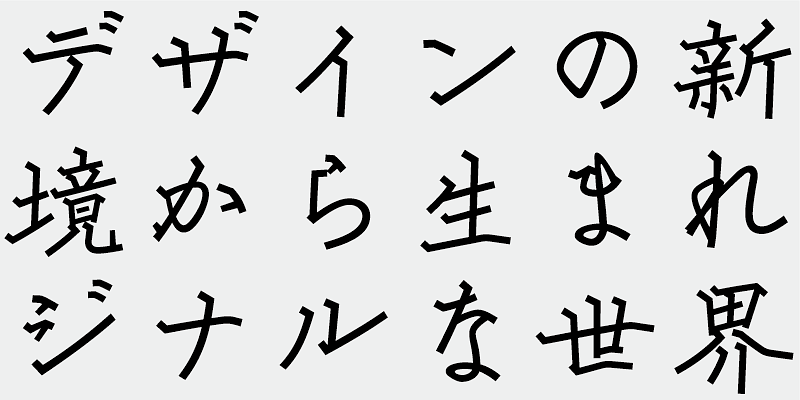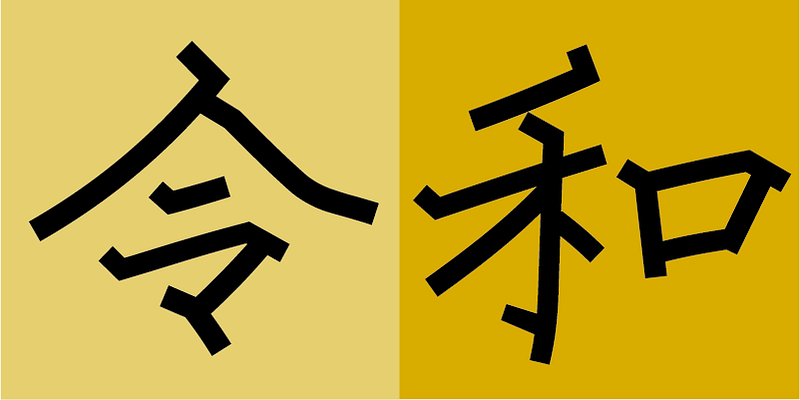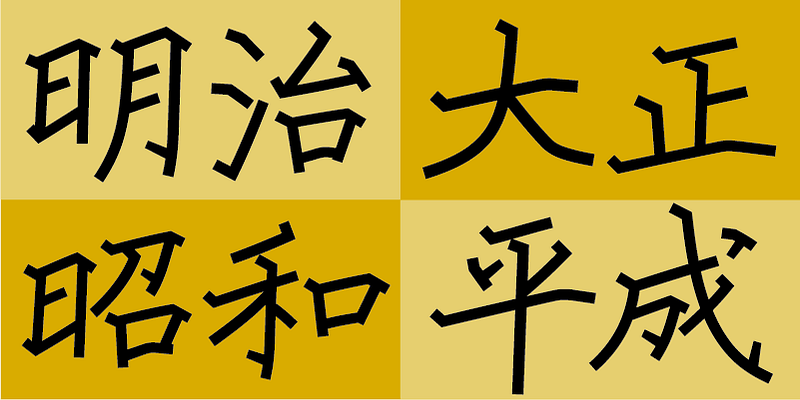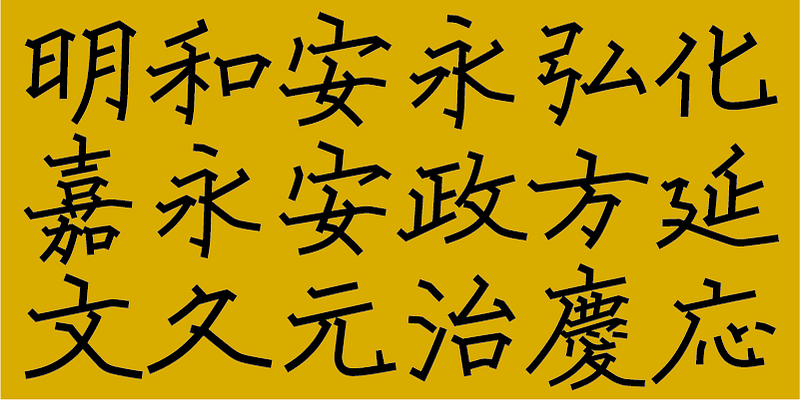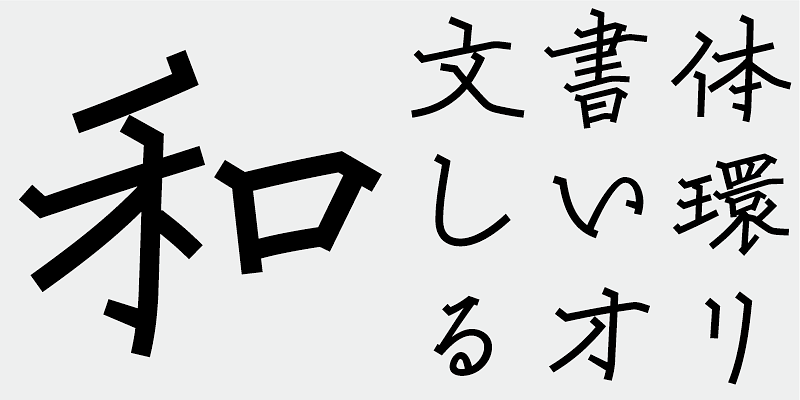
Kai ist eine elegante, maskuline gotische (serifenlose) Schriftart.
Sie weist lineare Strukturen auf, ist aber so gestaltet, dass die Glyphenformen sanft auslaufen. Die Kana-Zeichen basieren auf der Struktur der Kodo-ken Shincho-tai-Schrift.
Die jedem Zeichen innewohnende Form ist natürlich schön. Ob ein Zeichen breit oder schmal, klein oder groß ist, es ist so konzipiert, dass es in einen Kreis passt, da ein korrekt geschriebenes Kanji oder Kana-Zeichen dazu neigt, in einen Kreis zu passen. Wenn die visuelle Mitte jedes Zeichens sowohl in horizontaler als auch in vertikaler Richtung konsistent ist, werden Sie unabhängig von der äußeren Form des Zeichens schöne Schriftergebnisse erzielen.
Wenn zum Beispiel mehrere Zeichenelemente (wie Henne und Tsukuri) des 曇-Zeichens vertikal gestapelt oder nebeneinander in ein Quadrat gesetzt werden, wird die natürliche Zeichenstruktur verzerrt. Um dies zu vermeiden, stapeln wir die Zeichenelemente einfach übereinander oder stellen sie nebeneinander, auch wenn einige Zeichenformen eng zusammengedrängt werden oder ihre Größe (Bounding Box) sehr groß ist. So ist eine Buchstabenform natürlich aufgebaut.
Ein grundlegendes Merkmal einer gotischen (serifenlosen) Schrift ist, dass die Strichstärken optisch ausgerichtet sind. Verschiedene Zeichen benötigen unterschiedliche Strichstärken. Zeichen mit einer geringen Anzahl von Strichen wirken tendenziell größer und heller, während Zeichen mit einer großen Anzahl von Strichen eine höhere Dichte aufweisen und schwerer wirken, wenn sie mit Strichen gleicher Breite gezeichnet werden. Die Lücken zwischen den Strichen können beim Druck unerwünscht gefüllt werden. Bei diesem Entwurf ist die Dichte der wichtigsten Zeichenteile so ausgewogen wie möglich, anstatt gleichmäßig über das Ganze verteilt zu sein, so dass die Zeichen ihre eigenen, natürlichen und attraktiven Formen haben.
Diese Schriftart enthält 2.286 Zeichen aus der Joyo Kanji-Liste und Jinmei-yo Kanji-Zeichen sowie weitere 206 Zeichen, darunter Kana-Zeichen, Satzzeichen und lateinische Zeichen usw.
In der heutigen japanischen Schriftproduktion gelten die 7.000 Zeichen des JIS-Standards als unabdingbar. Aber brauchen alle Schriften wirklich 7.000 Zeichen? Im Zeitalter des Fotosatzes wurden weit weniger Zeichen benötigt. FONT1000, eine Gruppe unabhängiger Schriftdesigner, ging von dieser einfachen Frage aus. Wir haben die mindestens 1.000 (ideografischen) Kanji-Zeichen ausgewählt, die für den Satz in Japanisch erforderlich sind, und aktiv Schriften und Schriftbilder dafür entworfen. Dieser 1000-Kanji-Zeichensatz wurde unter Verwendung von Zeichenhäufigkeitsdaten ausgewählt, die u. a. von Zeitungsunternehmen, Verlagen und Sprachforschungsinstituten zusammengestellt wurden, und enthält auch Kana-Silbenzeichen und Satzzeichen. FONT1000 begann 2001 mit 25 Designern und 25 Schriften. Heute haben wir 130 Schriften und sind auf fast 40 Mitglieder angewachsen, sodass wir an Schriften mit mehr Zeichen arbeiten können.